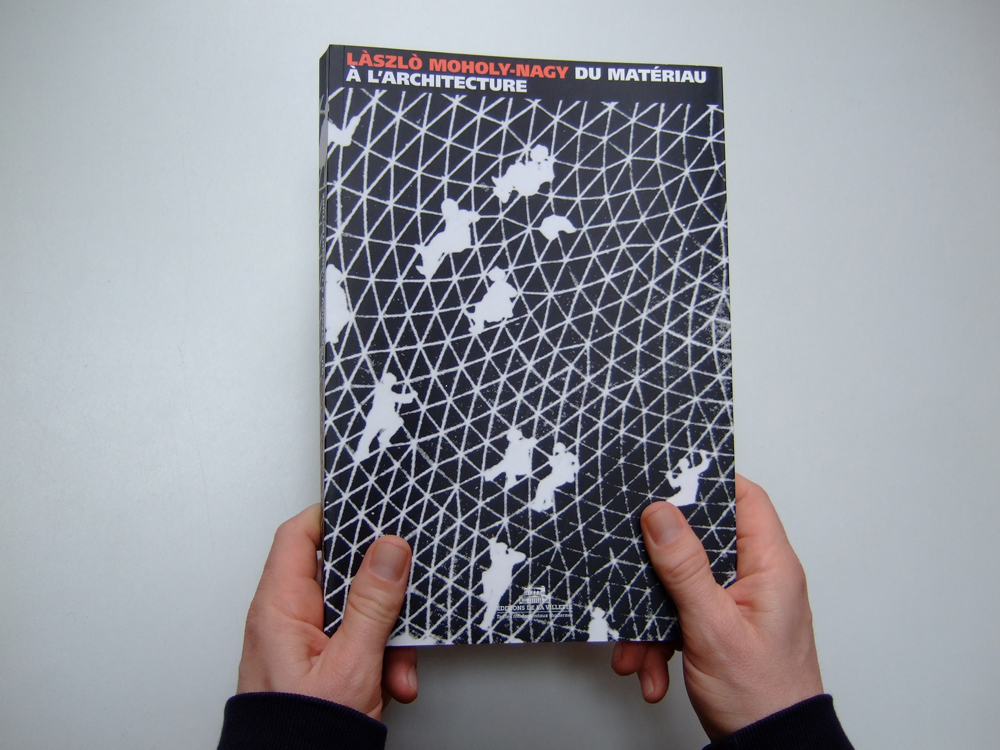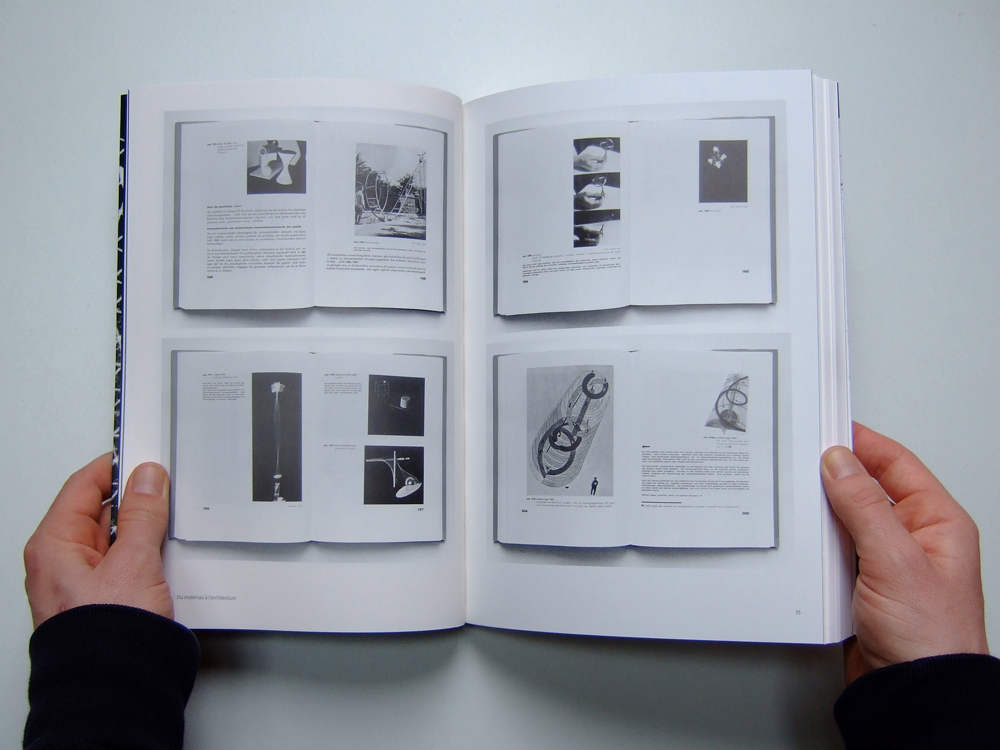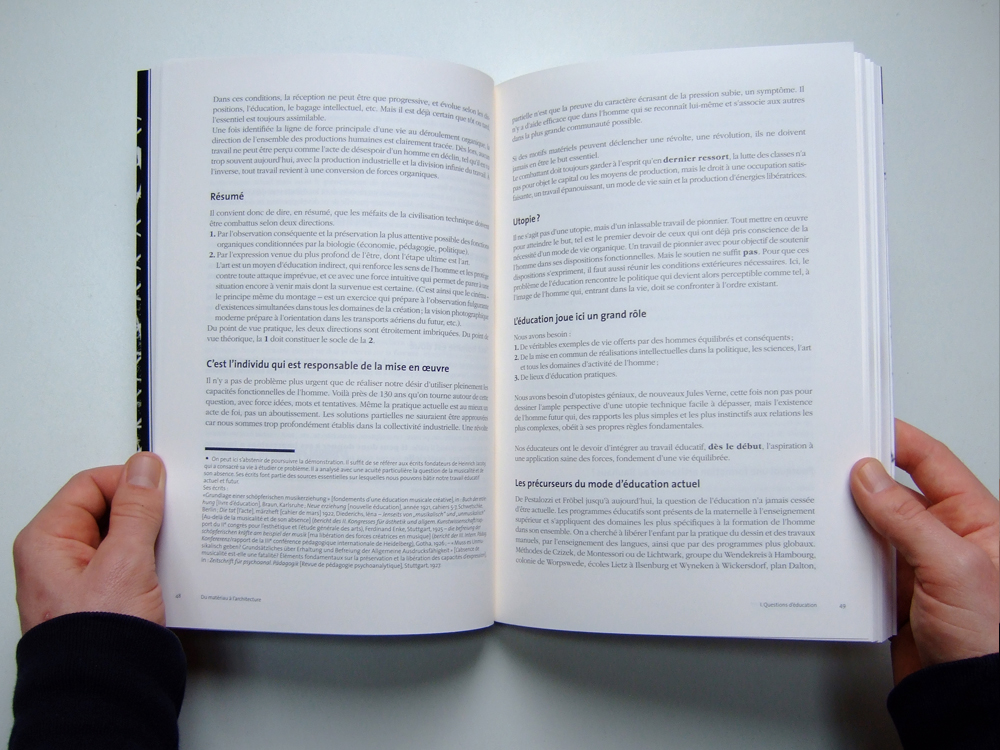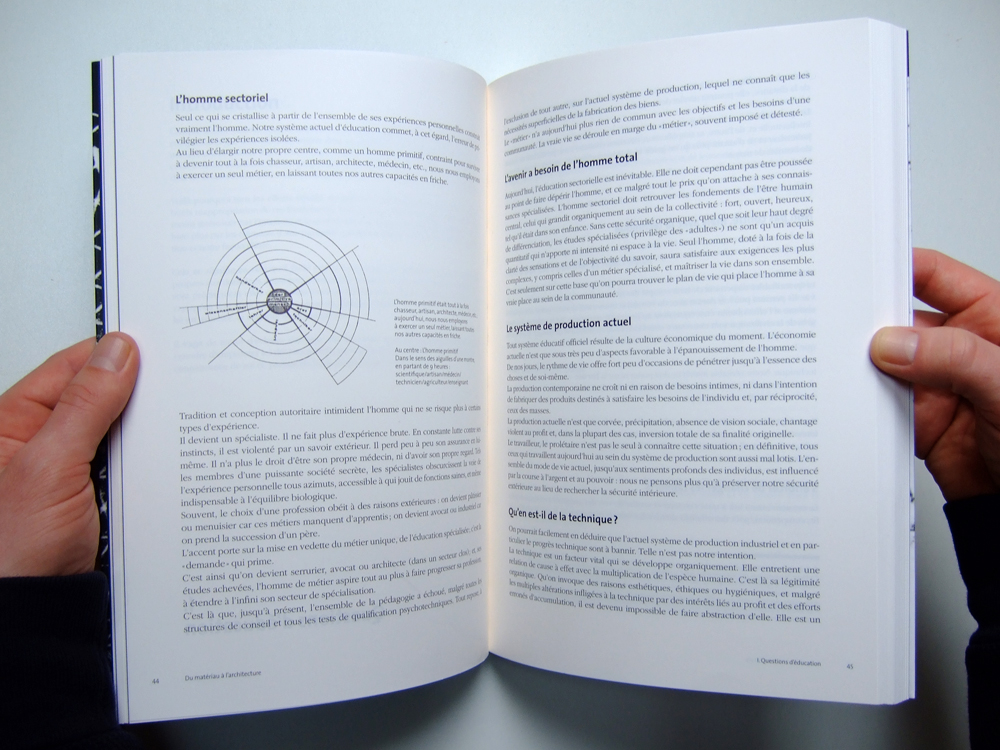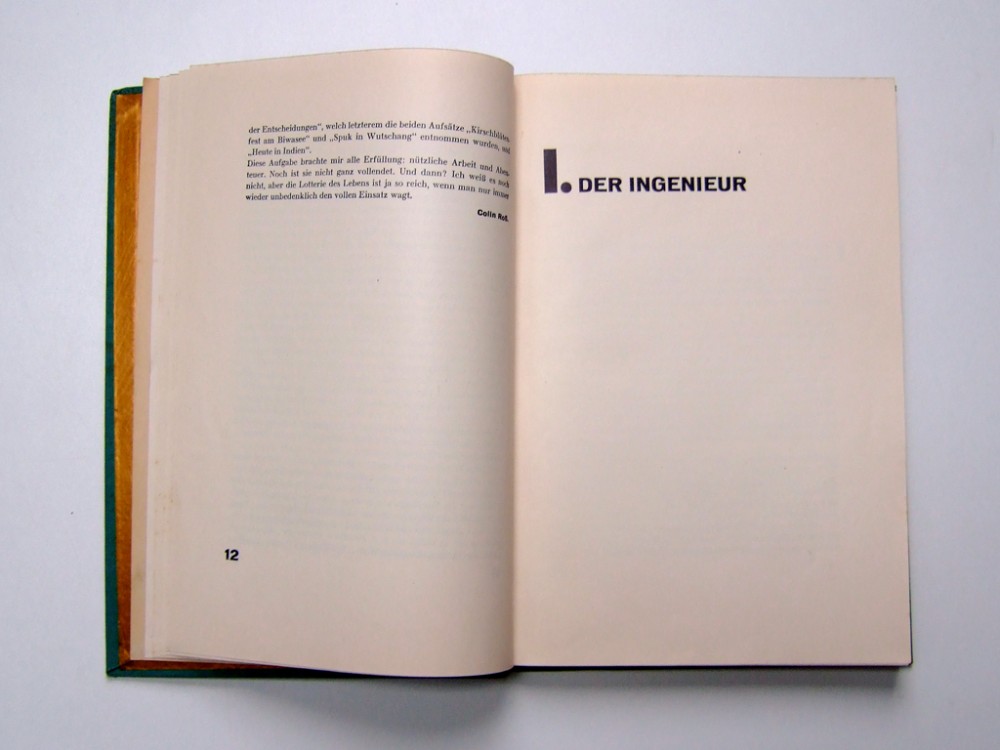
Des matériaux du livre à la typographie
Je n’ai pas l’habitude d’écrire à charge. Je préfère défendre les projets que j’aime. Les productions tristes, inintéressantes, épuisées… sont si nombreuses dans notre pays si peu enclin à considérer nos petites préoccupations du graphisme et de la typographie. C’est pourtant un hommage contrasté que je vais proposer aux éditions de la Villette au sujet de leur récente réédition de l’ouvrage décisif de László Moholy-Nagy Du Matériau à l’architecture.
László Moholy-Nagy  Du Matériau à l’architecture Éditions de la Villette 2015
László Moholy-Nagy
Du Matériau à l’architecture
Éditions de la Villette
2015
László Moholy-Nagy  Du Matériau à l’architecture éditions de la Villette 2015
László Moholy-Nagy
Du Matériau à l’architecture
éditions de la Villette
2015
D’abord il faut féliciter le projet ambitieux et nécessaire de traduction en français du dernier Bauhausbücher de 1929 Von Material zu Architektur. Il aura fallu attendre près de 80 ans pour que cet ouvrage acclimaté dès 1930 aux États Unis sous le titre The new vision et réédité quatre fois depuis, réimprimé de nouveau en Allemagne en 2001 dans la série des Neue Bauhausbücher, soit enfin disponible dans notre belle langue des lumières. Et cet ouvrage n’est pas du tout anodin : ultime production de cette collection d’éditions du Bauhaus qui comptait Oskar Schlemmer, Kasimir Malevitch, Wassily Kandinsky ou Paul Klee, l’édition se fait non seulement l’écho encore bien vivant du lieu primitif de nos disciplines des arts appliqués à l’industrie, à l’économie, à la vie, mais elle constitue surtout une sorte de testament. Le testament esthétique du plus jeune enseignant du Bauhaus, rédigé alors qu’il venait de quitter l’école notamment parce qu’il la sentait en voie d’académisation, sous les pressions des politiques de droite et d’extrême droite. Ce livre qui n’a pas été nommé dans sa version étasunienne The new vision pour rien, propose effectivement non seulement un succédané un brin hétéroclite de la pédagogie humaniste de László Moholy-Nagy, mais aussi toute la fraîcheur optimiste d’une esthétique. Une esthétique constructiviste teintée de dadaïsme expérimental et de machinisme bricoleur et organique, voire une morale de l’adaptation de l’homme « total » à l’industrie et à la modernité, via une nouvelle poétique de la vie des formes, de la lumière, des matériaux, de la technique et de l’expérience sensible. Il faut le dire, ce livre qui devait originellement s’appeler De l’art à la vie propose une leçon formidable.
Il faut ensuite féliciter l’énergie, la passion, la qualité de l’accompagnement théorique de cette parution au travers des interventions de Stéphane Füzessery, Pierre-Damien Huyghe, Elitza Dulguerova et Philippe Simay, qui se double d’une sensibilité inédite à notre discipline si souvent boudée dans les milieux universitaires.
Pour mettre en perspective la pensée de Moholy Nagy, Pierre-Damien Huyghe critique l’approche du design-dessein servile qui enfermerait l’expérimentation de la forme et de la technique dans un projet de service, dans un préconçu qui ne saurait pas prendre le risque et la richesse de l’exercice, c’est à dire de la découverte : de ce qui peut être sécrété, révélé dans le travail architectural du matériau1. L’exercice pédagogique de Moholy-Nagy, il apprendrait quelque chose et il proposerait une réalisation qui serait encore une machine à produire du sens, du possible. Il augmenterait les capacités de l’objet et de celui qui en fait l’expérience. Il serait, comme l’écrit Moholy Nagy un peu avant cette parution, l’objet d’une production et pas d’une simple reproduction2.
László Moholy-NagyDu Matériau à l’architectureéditions de la Villette2015 Note de l’éditeur
László Moholy-Nagy
Du Matériau à l’architecture
éditions de la Villette
2015
Note de l’éditeur
Stéphane Füzessery et Pierre Simay écrivent que « quiconque ouvre le livre ne peut qu’être frappé par la richesse des matériaux illustratifs, par le soin extrême apporté par Moholy à la composition de chaque page et aux rapports entre texte et image, ou encore par la singularité des choix typographiques : ceux-ci comptent autant sinon plus que le contenu discursif du texte d’accompagnement »3. On se prend à rêver d’une forme graphique soudain réellement prise en compte et d’autant que Moholy Nagy était non seulement, avec Walter Gropius, le directeur de publication des Bauhausbücher mais aussi leur graphiste en chef. Et nous nous sentons exaucés quand Elitza Dulguerova, dans une conversation à l’occasion du lancement de l’ouvrage4 assure que la traduction française sera « fidèle à la mise en page et à l’objet livre allemand » ainsi qu’à ses valeurs critiques. D’autant plus que Philippe Simay se félicite que les éditions de la Villette aient pris l’option de réaliser un « fac-similé de l’œuvre originale, de retrouver le livre exactement comme Moholy, théoricien de la double page et de la typo-photographie l’avait conçu et mis en page ». Une attention qui semble confirmée par la présentation, dans l’ouverture de la traduction française, de photographies de la merveilleuse édition originale et d’une note d’éditeur promettant de « conserver dans la mesure du possible – nous soulignons en même temps que nous nous interrogeons sur la nature de cette mesure – la mise en page originale et le rapport texte-image imaginé par Moholy Nagy ».
Raum der Gegenwart, 1930, conçu par Alexander Dorner aet Lászlò Moholy Nagy, realisé par Kai-Uwe Hemken et Jakob Gebert. vue de l’installation au Abbemuseum, 2010.
Une des caractérisques des compositions typographiques de la neue typografie, au delà des textes non justifiés respectant les réglages optiques des typographies, au delà de la prédilection du système des différences de la bas de casse qui va jusqu’à interdire toute hiérarchisation à l’antique de la capitale toujours vaguement lapidaire et romaine, c’est une machine optique constructiviste qui fonctionne grâce au contraste exacerbé de matériaux visuels réduits, concentrés, comme une pile, comme un moteur. Une structure forte des différences privilégiant les effets de décentrement afin d’autoriser, de susciter, la plus grande liberté de mouvement des yeux et de l’esprit. Et de la double page à cet autre espace de vision qu’est la machinerie d’exposition, il faut sans doute se rappeler que Moholy Nagy, artiste appliqué total, travailla en 1930 à la réalisation d’une Gegenwart5 avec Alexander Dorner, directeur du musée de Hanovre qu’il considérait comme un « nouveau type de structure ressembl[ant] davantage à une centrale électrique, à un créateur d’énergies nouvelles ».
Jan « Ivan » Tschichold, Colin Ross, Das Fahrten und abenteuer buch, Büchergilde Gutenberg, Leipzig, 1925
Dans le traitement macrotypographique du Bauhausbücher de 1929, la page confronte en tension des blocs textes assez denses et cohérents dans le rapport titre / bloc texte à des photographies dans des formats généreux et à de belles marges harmoniques libres de texte courant. Des marges du reste étonnamment encore assez conformes au vieux canon du codex. Les choix microtypographiques confrontent une grotesque de titrage assez discrète dans ses mouvements à une typographie à empattements de labeur au dessin assez contrasté, peut-être un « romain moderne », une didone comme peut nous y faire penser un Büchergilde Gutenberg mis en forme de façon analogue dans les mêmes années par Jan « Ivan » Tschichold, un autre garant fameux de la neue typographie. Titrage et caractère de labeur partagent le même corps et assurent un gris typographique homogène. Comme chacun des éléments du paratexte, folio, filet, appel de note, flèche-manicule, le texte est traité avec force et autonomisation comme un objet à part entière qui vient graviter dans l’espace blanc de la composition de la double page qui est d’abord une machinerie optique constructiviste.
3. Stéphane Füzessery et Pierre Simay, Préface, « De l’art à la vie », László Moholy-Nagy, Du Matériau à l’architecture, Éditions de la Villette, Paris, 2015, p. 15 [↩]
5. d’une Salle du présent [↩]
6. malgré le travail récent sérieux d’identité générale de Change is Good [↩]